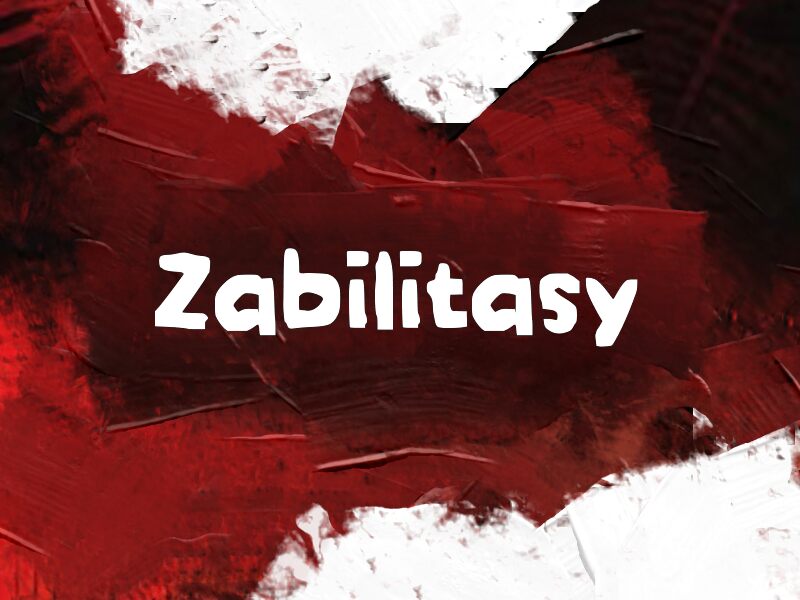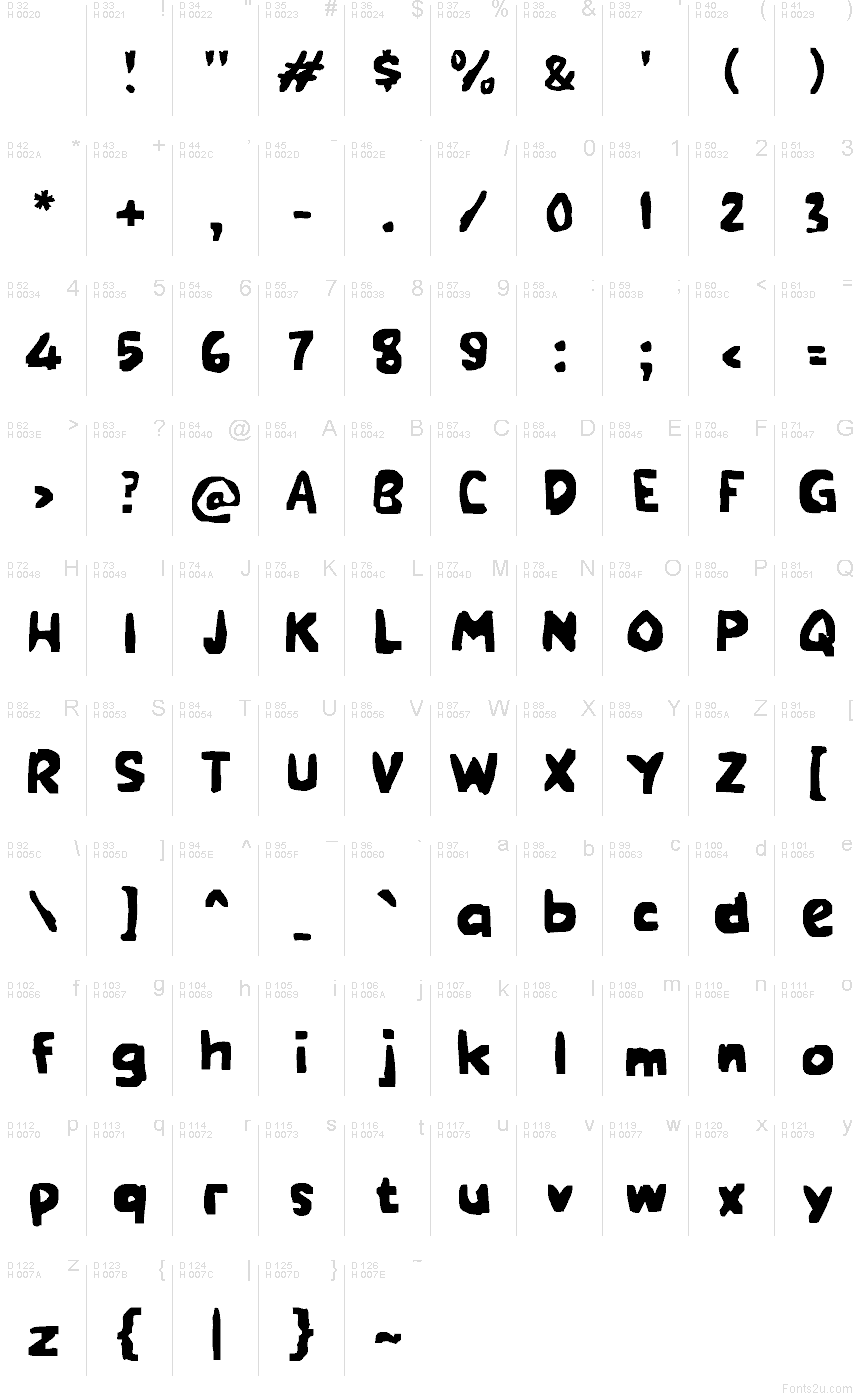
Zabilitasy
Zabilitasy - бесплатный акцидентный шрифт от Wep, вдохновленный мультяшной стилистикой. Его неровные, «рубленые» очертания делают буквы похожими скорее на нарисованные вручную формы, чем на стандартную типографику. Широкие штрихи, скругленные углы и слегка дрожащие вертикали придают ему домашний, живой характер, а компактная расстановка сохраняет целостность дизайна, не позволяя ему стать небрежным.
Этот дерзкий и фактурный стиль идеально подходит для детских плакатов, упаковки снеков, комиксных заголовков, школьных меток и игровых графических материалов для соцсетей, где излишне строгий шрифт смотрелся бы неестественно. Короткие заголовки особенно выигрывают от этого энергичного ритма, который придает каждому слову визуальную весомость без использования дополнительных эффектов.